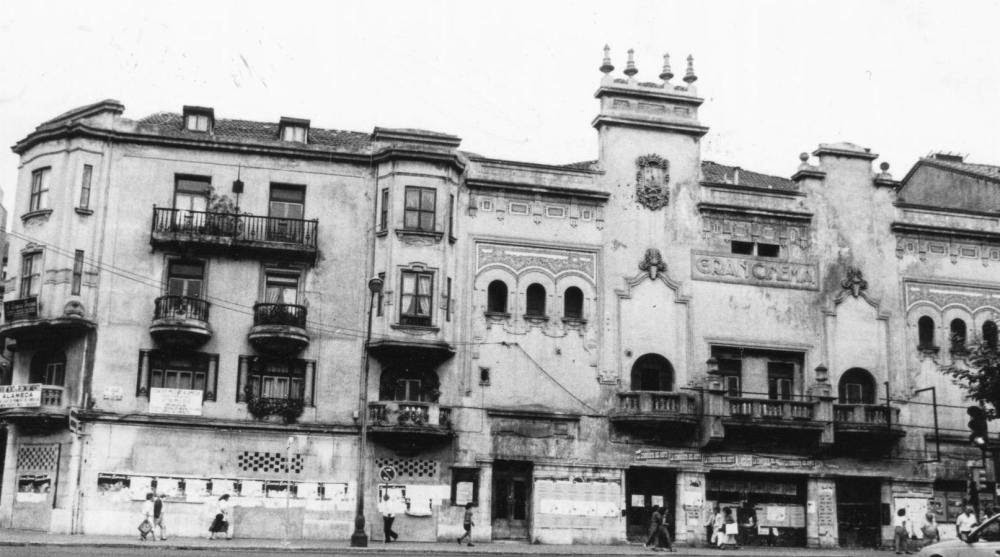
Gran Cinema
En lo que hoy es la actual sede de la ONCE, en la Calle Burgos, antaño acogió uno de esos cines míticos de Santander. Aunque diversas fuentes no fijan la fecha de apertura, si es cierta que ya en hacia los años 30 estaba en activo como sala de teatro y cine. A finales de los 90s cerraron y el edificio se derribó, respetando su fachada protegida. Donde hoy está el rótulo de la ONCE, se ubicaba esas letras que hoy dejamos reproducidas aquí.
PD: Las diversas fotos manejadas, no dan detalle de la tipografía dada la calidad de las mismas, siendo esta reproducción lo más fiel a las fotos existentes y a la época; si alguien dispone de alguna imagen con más detalle, me gustaría que me lo hiciese llegar para poder perfeccionar esos matices que seguro esconden estas letras 🙂